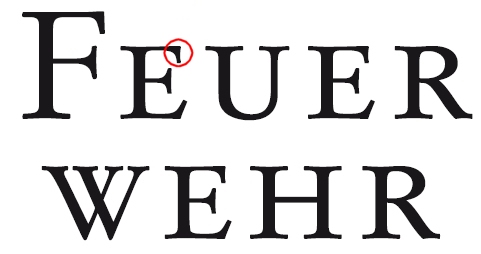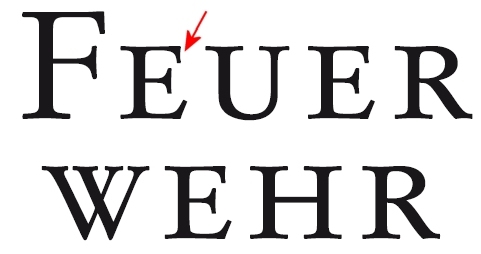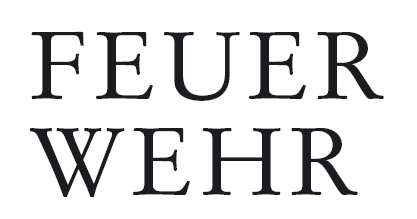
Beinahe Garamond, aber nicht ganz
Weiss jemand welche Schrift im folgenden Bild verwendet wurde?
Ich komme nicht weiter. WhatTheFont und Identifont kommen immer auf "Garamond" oder "Stempel Garamond" aber das E stimmt nicht genau überein.
Jetzt ist es klar! Passt genau.
Es ist die "Stempel Garamondâ„¢ Roman SC" (Linotype Originals)